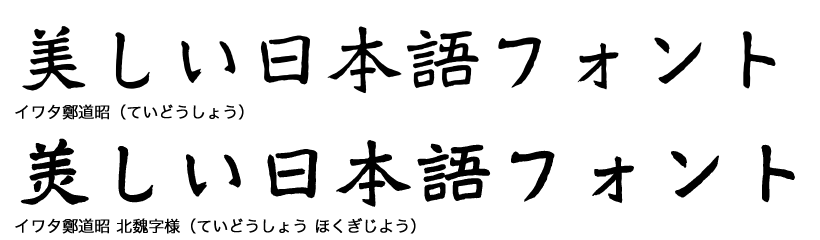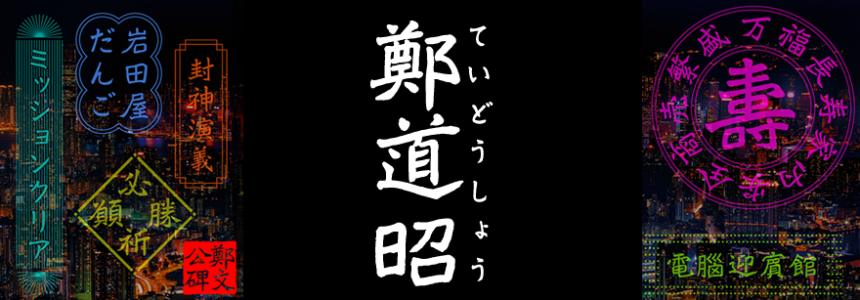
イワタ新書体「鄭導昭」のご紹介
「イワタ鄭道昭」とは、実在した書家の名前そのものが書体名になったフォントです。
「鄭道昭」は中国の北魏(ほくぎ=西暦500年ころ)の時代に活躍した書家で、中国山東省の雲峰山などの岩壁や巨石に雄大で力強い文字を残しました。
その書体デザインをデジタルデータで再現。
【特長】
1500 年前、中国雲峰山の岩壁に刻まれた鄭道昭の書が現代に蘇る、摩崖碑の風化や岩肌のニュアンスを封じ込めた書体。
書家・大庭紀霽氏によって書き下ろされた、ゴツゴツとした力強さの中に、のびやかな骨格の優しさが光る独特のバランス。
雄大な自然や筆の息遣いまで感じる、圧倒的な存在感を放つ書体です。